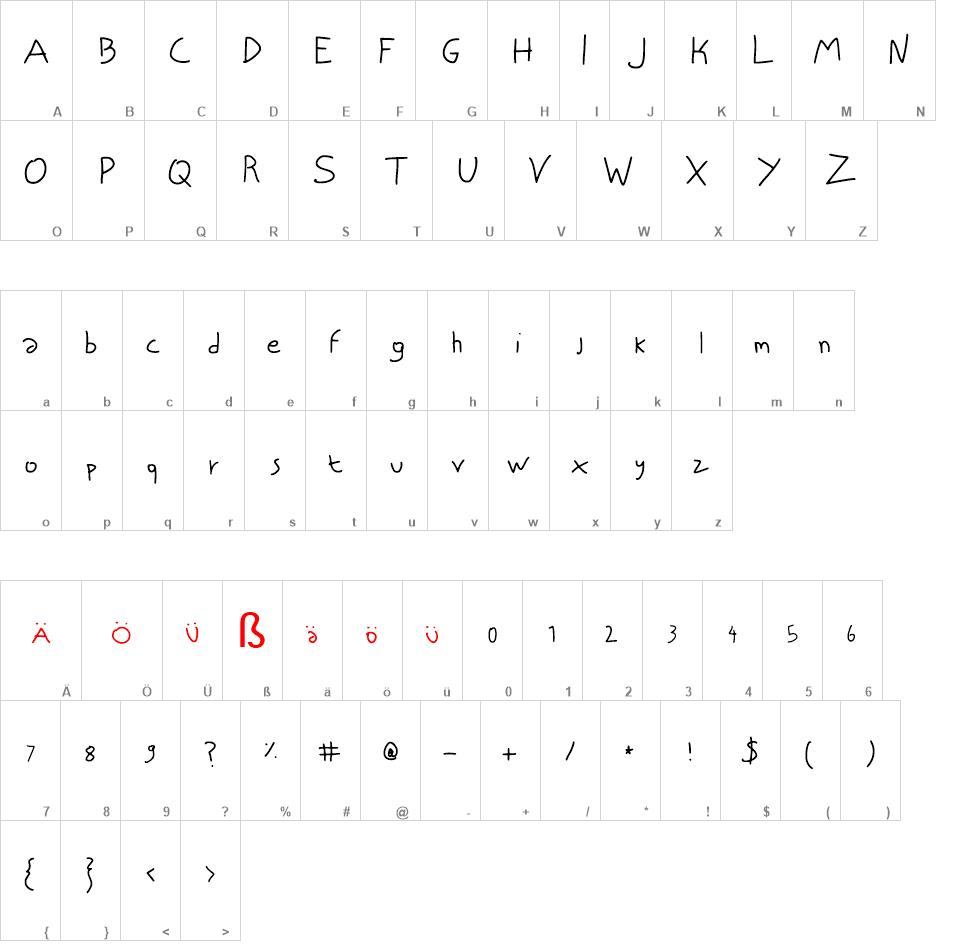
Niscript
Niscript font
Niscript
Russisch, Latein und ein mathematisches Symbol.
Diese Schriftart emuliert meinen Handschriftenstil; Ich brauchte es für ein Projekt und dachte, es könnte Spaß machen, es von jemand anderem benutzt zu sehen.